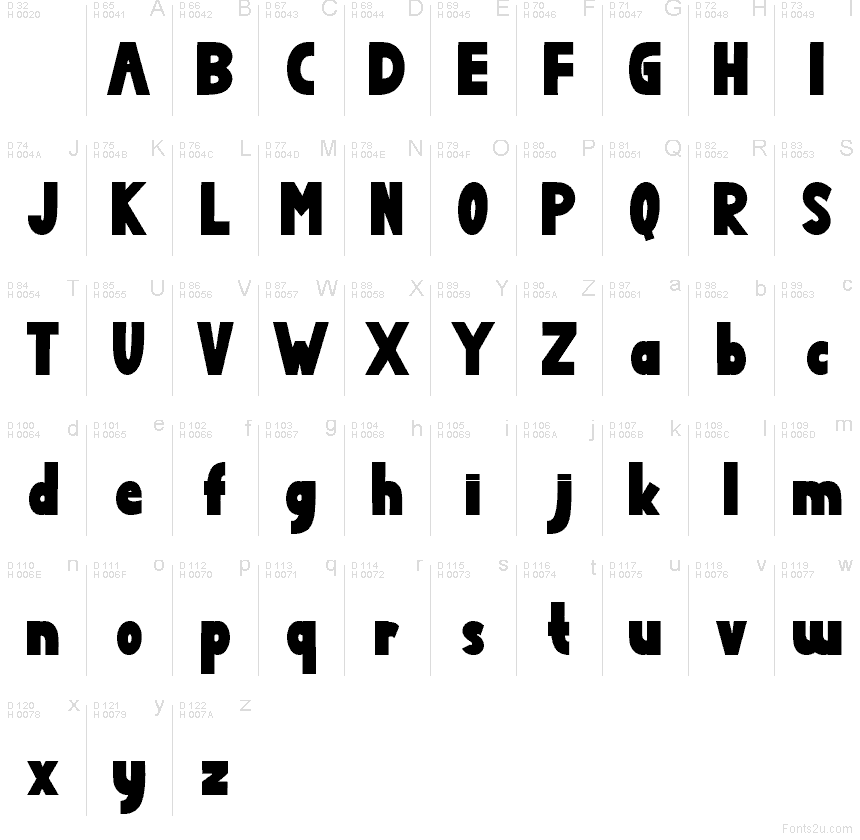
Flower Spring Monogram
Flower Spring Monogram de Yoga Letter es una tipografía display gratuita de estilo cómic, que destaca por sus formas redondeadas y un toque delicado de monograma. Sus letras presentan curvas suaves, contraformas abiertas y un ritmo constante que aporta al diseño un aire amable y artesanal, sin perder la legibilidad.
Flower Spring Monogram funciona de maravilla en invitaciones para eventos de primavera, logotipos florales, packaging creativo, gráficos para redes sociales, pegatinas y títulos decorativos para pósteres. Esta fuente gratuita es ideal para proyectos que requieren un acento alegre e informal, pero con la estructura necesaria para lucir impecable en monogramas, branding y textos cortos.